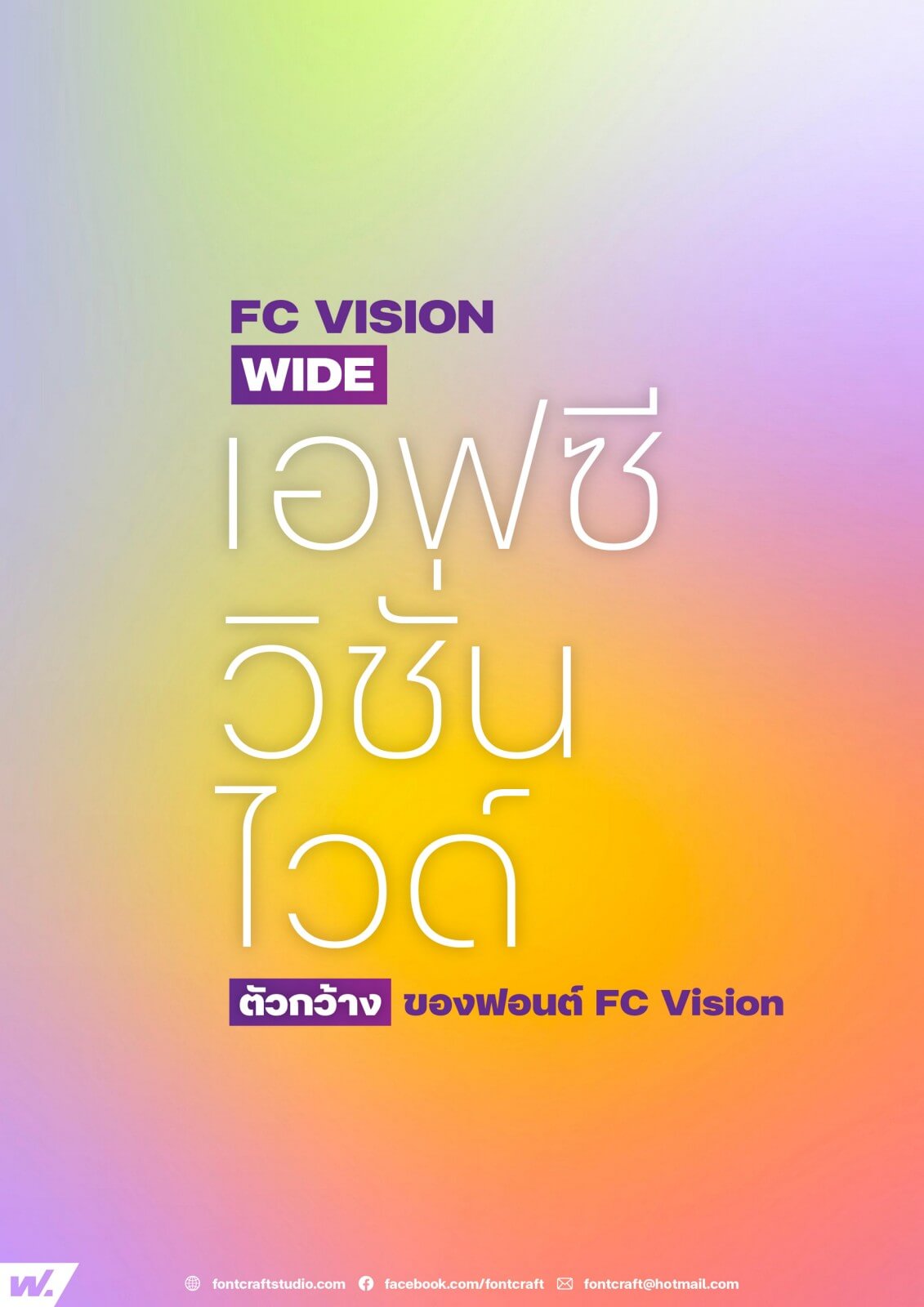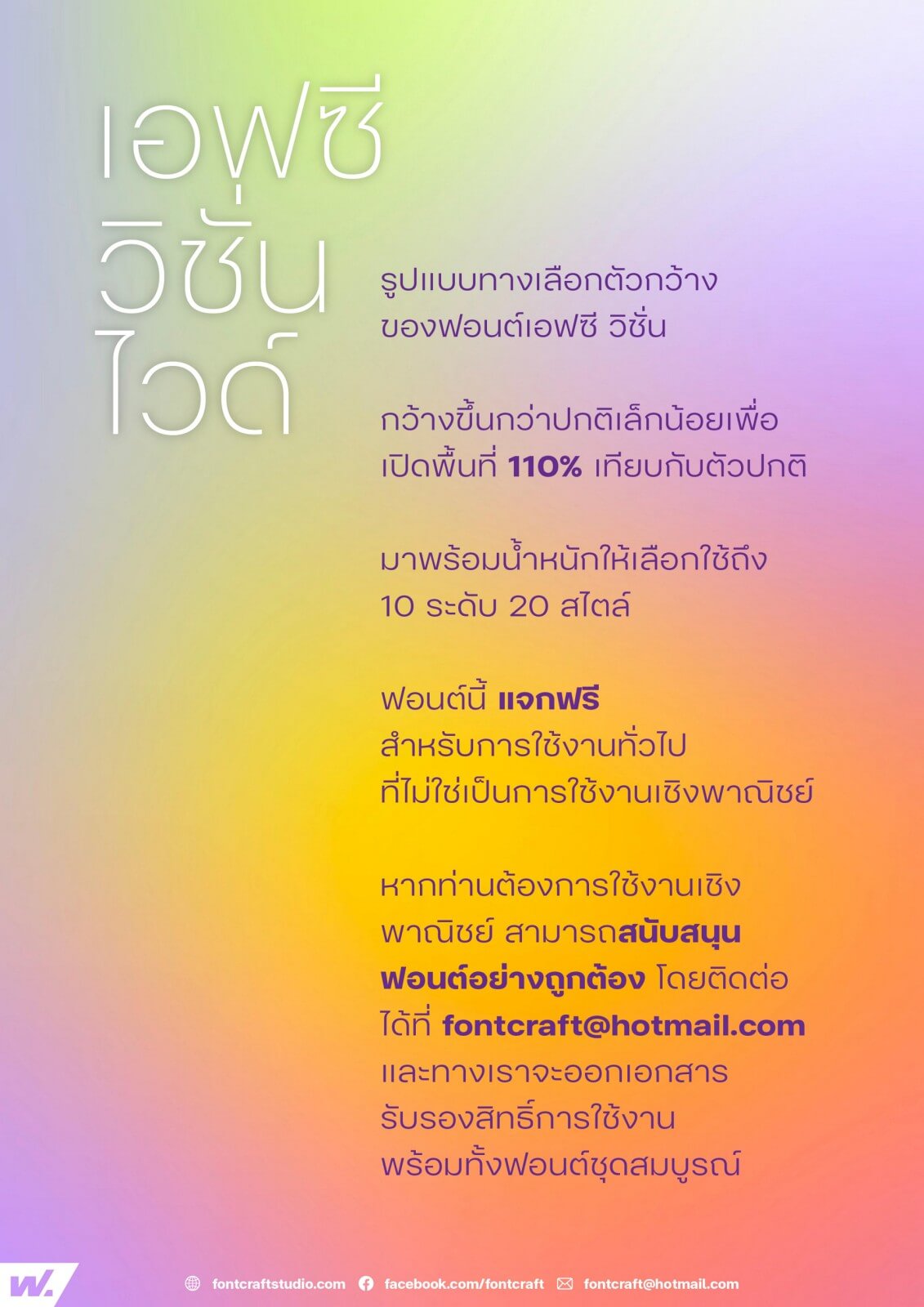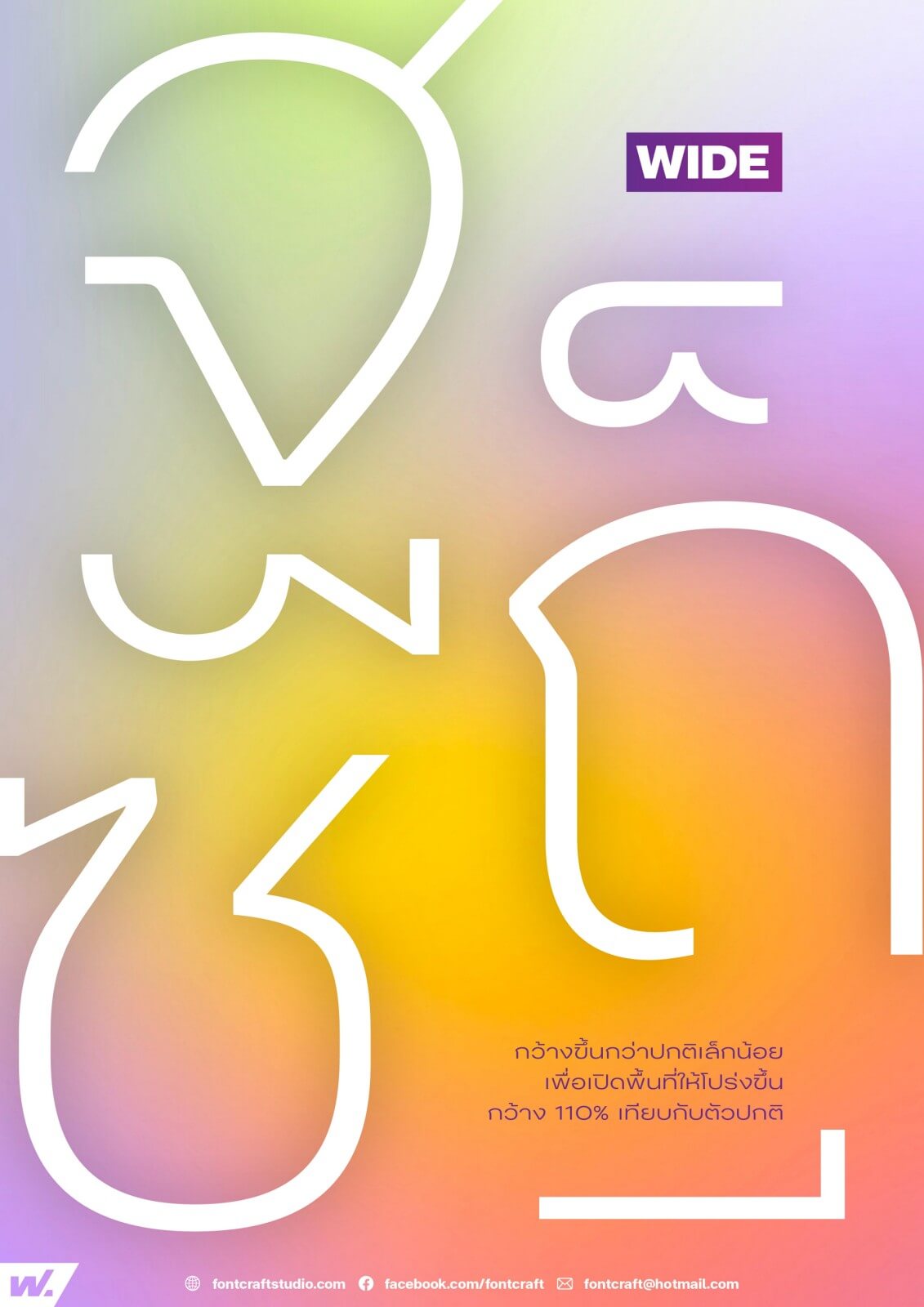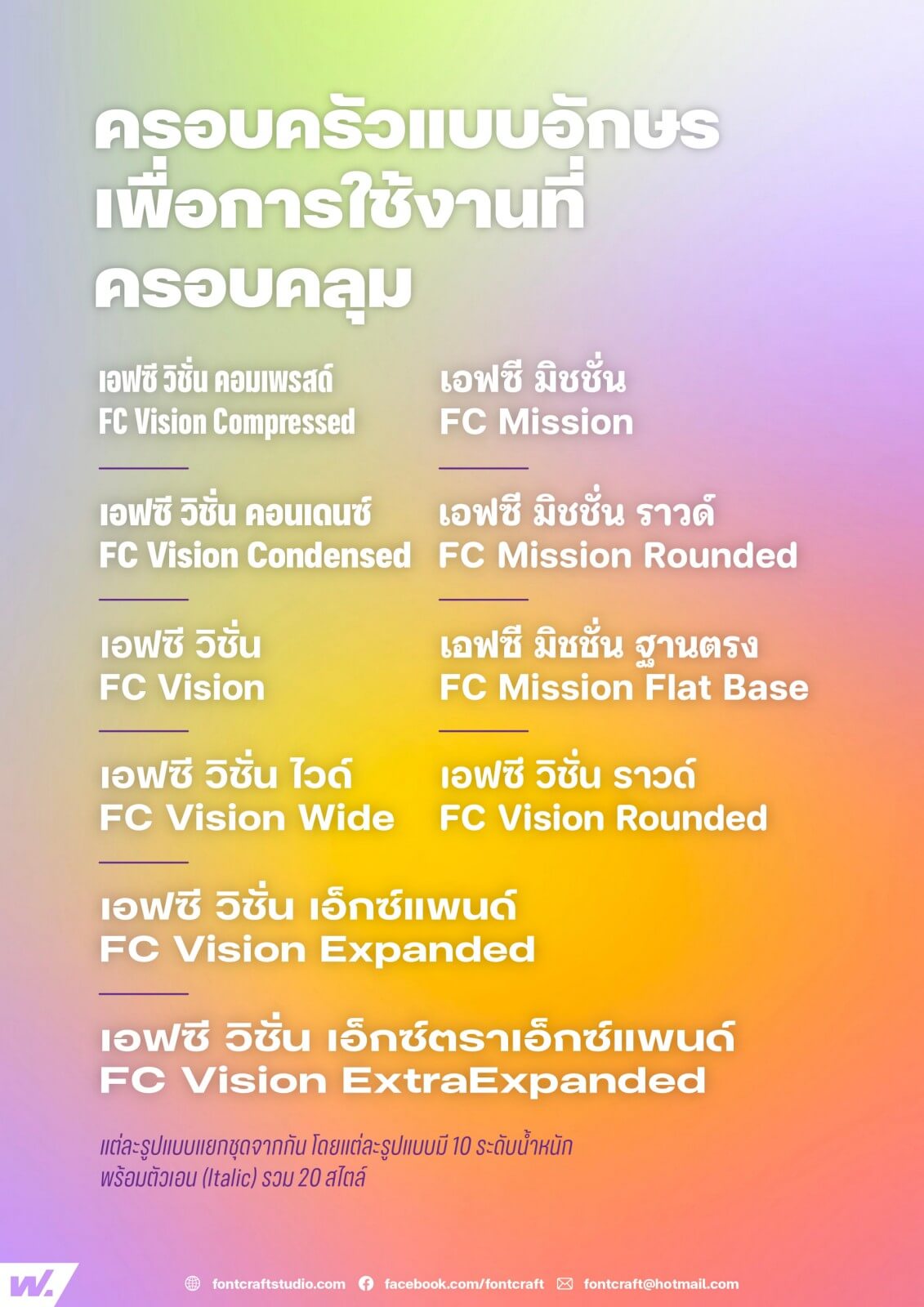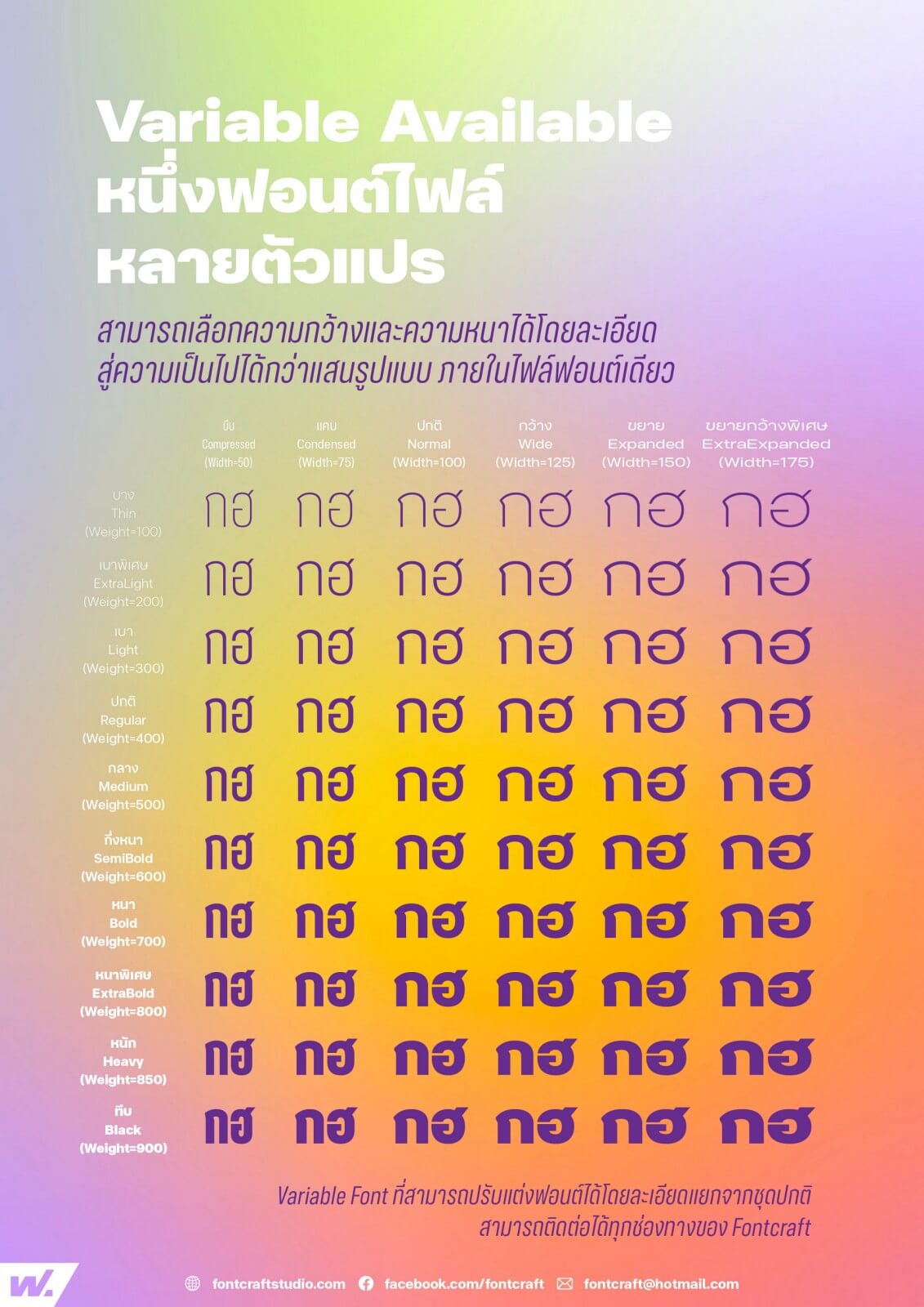
เอฟซี วิชั่น ไวด์ (FC Vision Wide)
รูปแบบทางเลือกตัวกว้างของฟอนต์ FC Vision Superfamily กว้างขึ้นกว่าปกติเล็กน้อยเพื่อ เปิดพื้นที่ 110% เทียบกับตัวปกติ